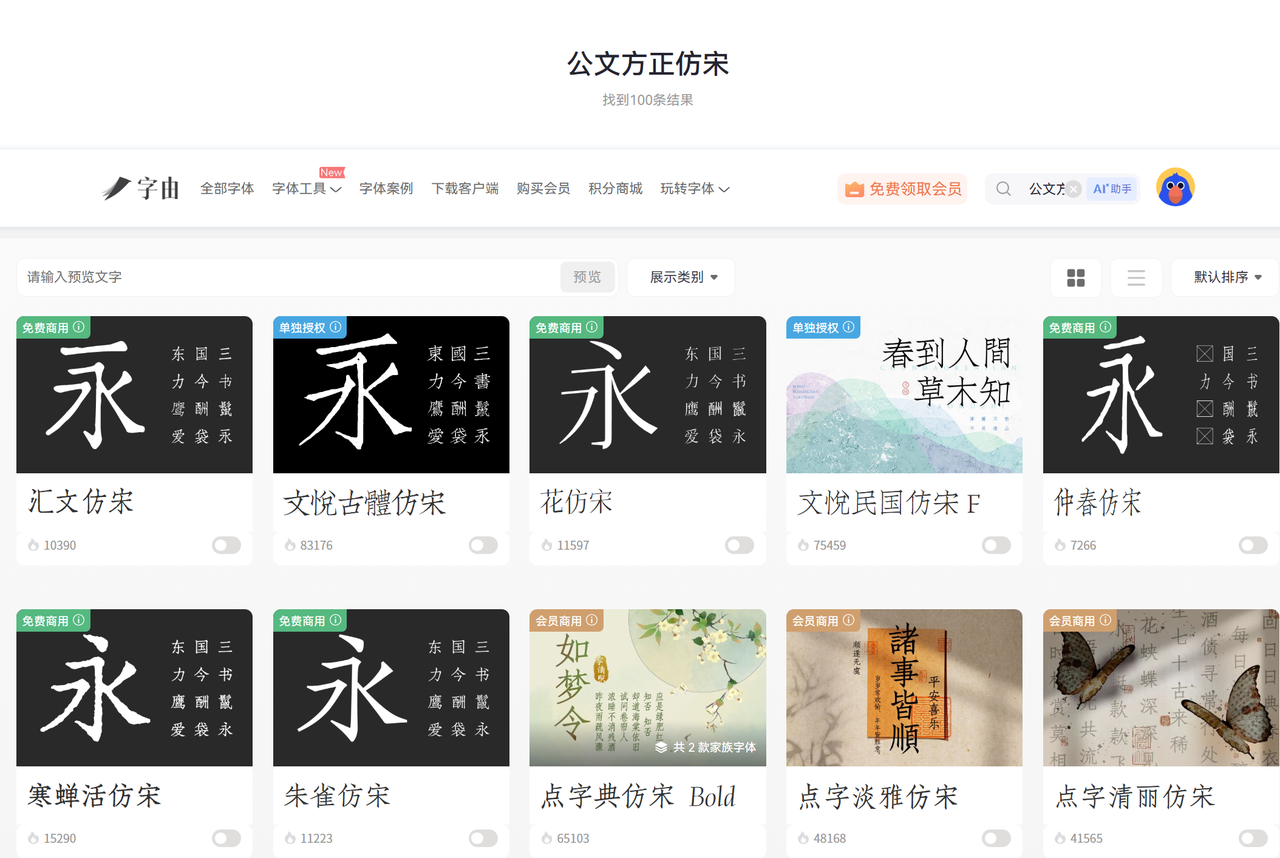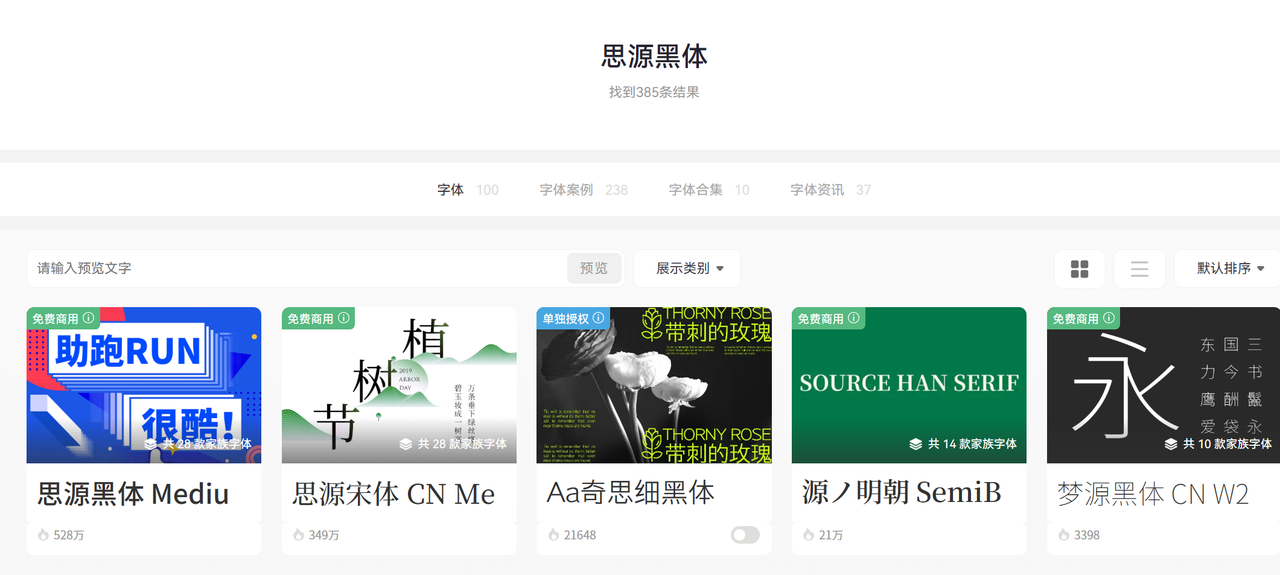
标准公文字体去哪找?4个靠谱下载网站推荐
公文写作对字体有着严格规范,《党政机关公文格式》明确要求正文用3号仿宋_GB2312,标题用2号方正小标宋,黑体、楷体亦有指定使用场景。不少人在办公时会陷入“找不到标准字体”“怕用盗版侵权”的困境,盲目搜索还可能下载到带插件的恶意文件。今天就分享4个经过实测的靠谱网站,从基础免费到专业授权全覆盖,帮大家高效搞定公文字体需求。
1. 字由网:办公党首选的字体管理神器
这是很多人现在办公离不开的字体神器,不光设计师爱用,职场写公文的人用了都夸方便。它不像普通下载站只堆资源,公文刚需的方正仿宋、黑体、楷体,一搜就有,不用翻页找半天。每款字体都标清了授权范围,免费商用的都有官方背书,正式公文印刷、线上报送都能放心用,会员解锁的正版字体,还能满足企业对外函件的严格要求。
结合公文排版的规范性要求,我筛选出字由平台上最常用、最适配的几款公文字体。第一款是方正仿宋(公文首选,规范标杆)作为公文排版的“标配字体”,适用于政府红头文件、政策通知、正式公文正文、发文字号、主送机关等核心公文模块,是最通用、最合规的公文字体。字由平台可直接激活使用,需查看具体授权说明,大部分版本是支持免费商用的
第二个思源黑体也是字由平台上最受欢迎的公文字体之一,适用于公文标题、小标题、工作总结、汇报材料、政务信息公开文件等,其不同字重可灵活区分公文层次,适配多种排版需求。有的字体可以免费商用有的是单独授权,使用时要注意喔~
最后一个思源宋体在字由网是也可以免费商用,排版整齐美观,自带传统公文的严谨气质,同时兼顾现代阅读的便捷性,适合需要体现传统文化底蕴的正式文档。
2. 方正字库官网:公文标准字体源头阵地
要论公文字体的规范性,方正官网认第二没人敢认第一——毕竟很多公文标准字体本身就是方正出品的。它专门设了“免费字体”专区,把公文必备的方正小标宋简体、方正仿宋_GB2312、方正黑体、方正楷体这四款直接摆出来,不用筛选,点进去就能下,完全贴合格式要求。这里的字体都是官方原版,字形够标准。
3. 站酷字库(免费专区):小众合规字体补充库
站酷是设计师聚集地,它的字库专区藏着不少宝藏免费字体,适合不想让公文排版太死板的朋友。除了基础的公文字体,还能挖到一些设计师授权的创意宋体、楷体变体,比如做年度总结、工作汇报时,正文用标准仿宋,副标题用小众合规楷体,既不违规又能有点设计感。
4. 阿里巴巴普惠体官网:免费商用的通用之选
阿里妈妈的普惠体,堪称免费商用字体里的“万能选手”。虽然不是公文指定字体,但胜在合规无限制,字形规整、辨识度高,日常的工作简报、内部通知、公文附件用它完全没问题,不用纠结格式细节。对于追求高效、零成本用字的职场人来说,性价比拉满。适合对公文格式要求不极致严格,主打一个省心高效的场景。